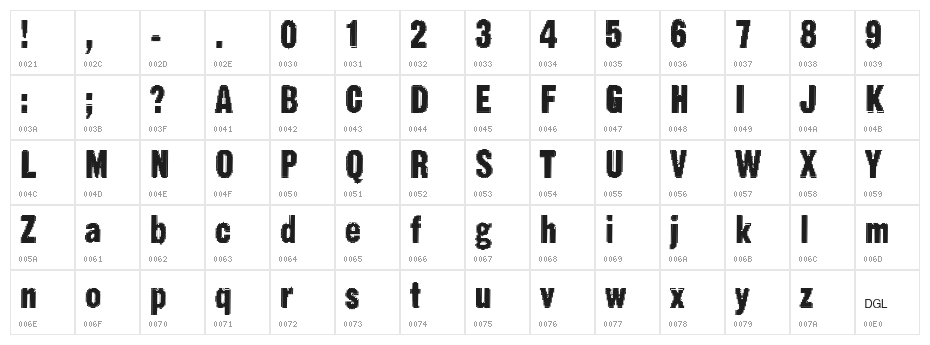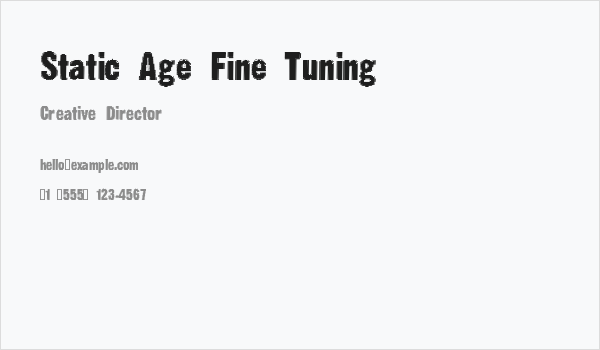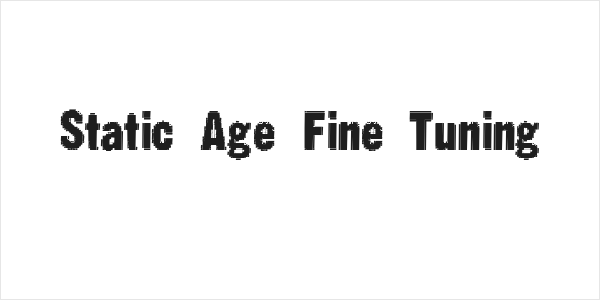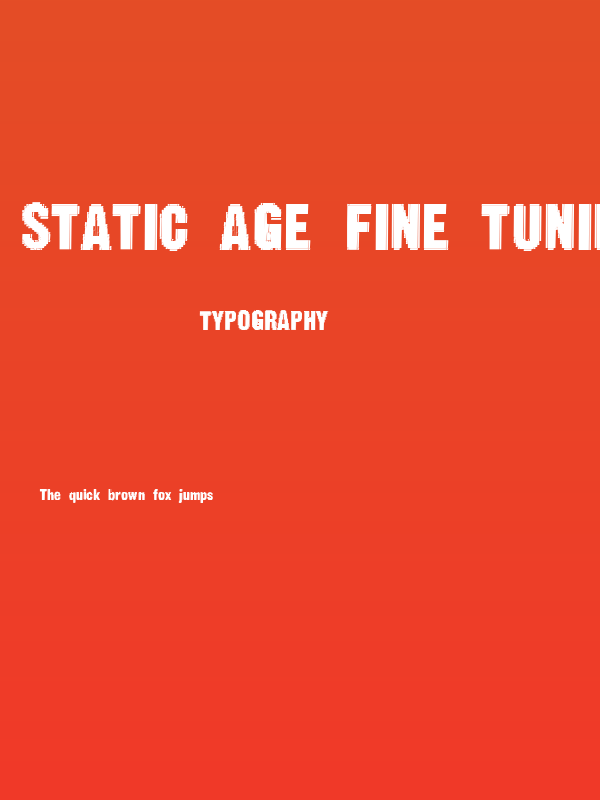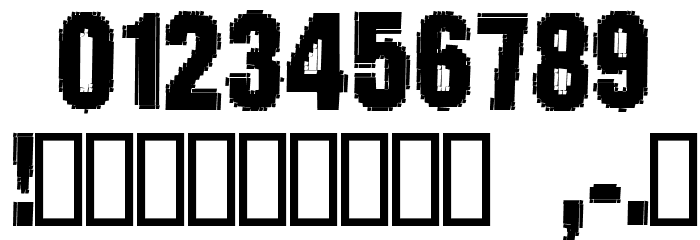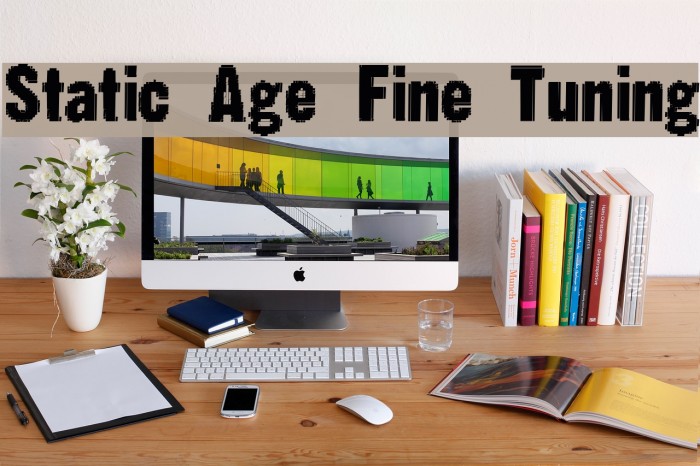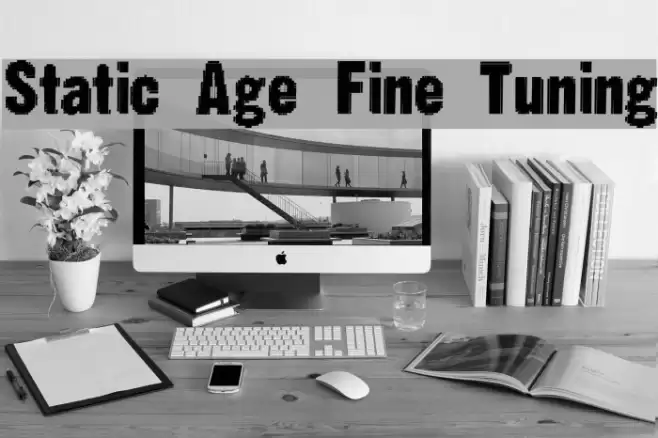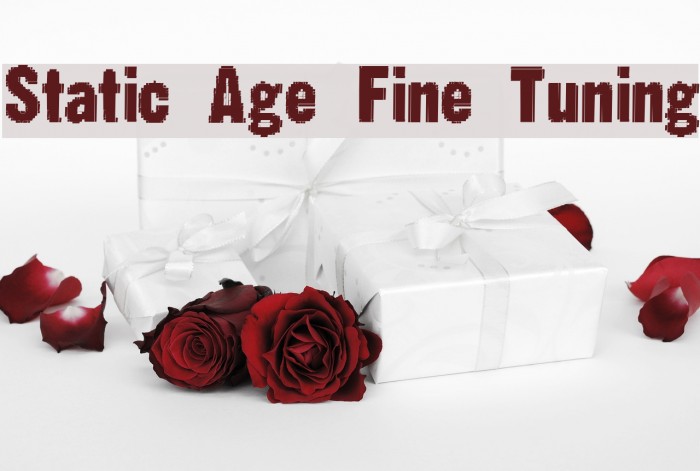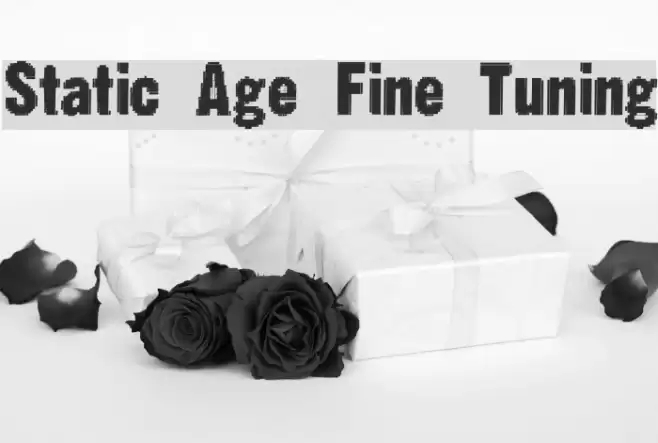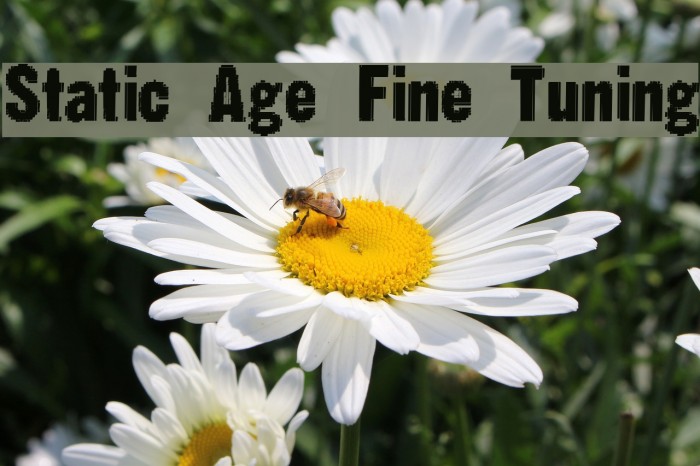
Static Age Fine Tuning Font
| Gesamtstil | Vintage, Grunge |
| Vorgeschlagene Projekte | Ideal for album covers, posters, branding for edgy or retro-themed products, and any design needing a bold, impactful look. |